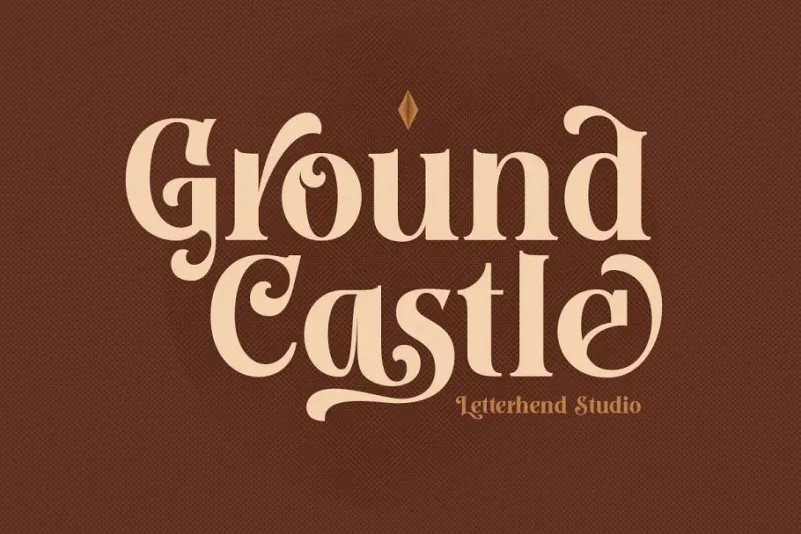
A ‘Ground Castle Font’ é uma escolha perfeita para aqueles que desejam adicionar elegância a seus projetos digitais. Inspirada no estilo serif moderno, esta fonte moderna e bold possui múltiplas ligaturas, tornando-a ainda mais única e distintiva. Além disso, seu estilismo alternativo complementa perfeitamente este aspecto único. Esta seleção de 99designs está idealmente equipada para uso em logotipos e outras formas formais como convites, rótulos, marcas, magazines, livros, cartões de cumprimentos ou casamentos, embalagens, moda, maquiagem, papelaria, novelas, selos ou qualquer tipo de propósitos publicitários. Sua personalidade forte e distintiva a torna ideal para estilos formais exigentes onde requere uma aparência elegante e sofisticada. Adquirindo esta fonte serif da Ground Castle, você estará garantindo um toque especial em seus projetos visuais, oferecendo a perfeita combinação de estilo moderno e robustez clássica. Seja para qualquer aplicação formosa ou comercial, esta ‘Ground Castle Font’ é uma excelente escolha para criar designs memoráveis e eficazes.